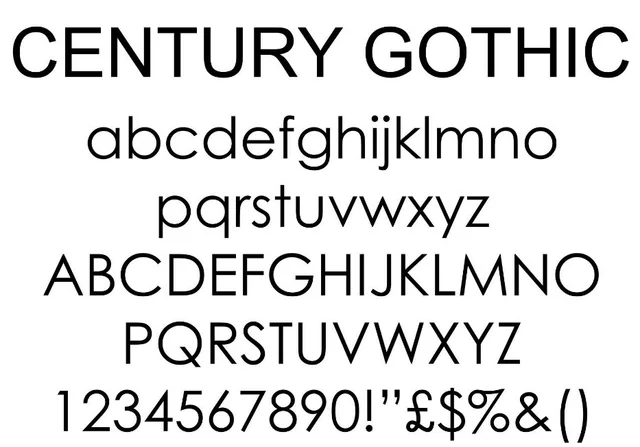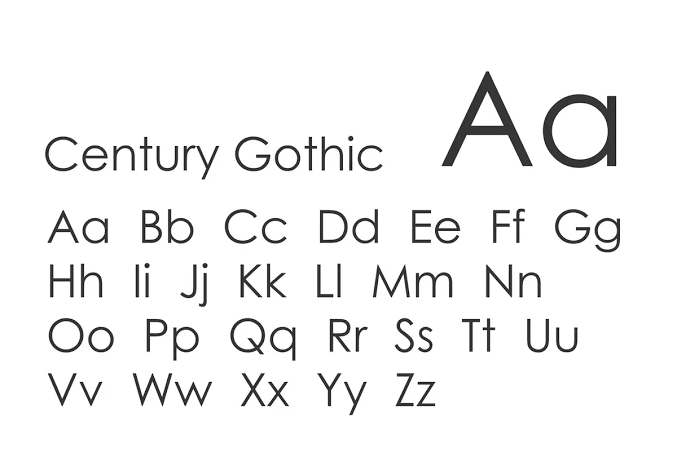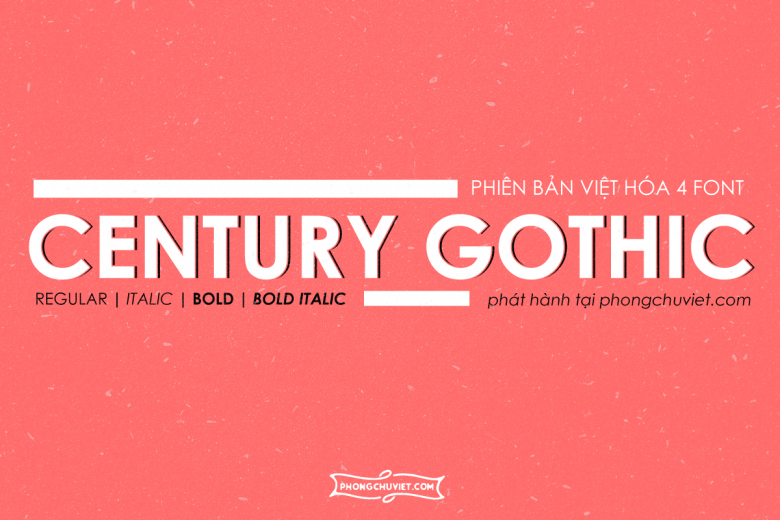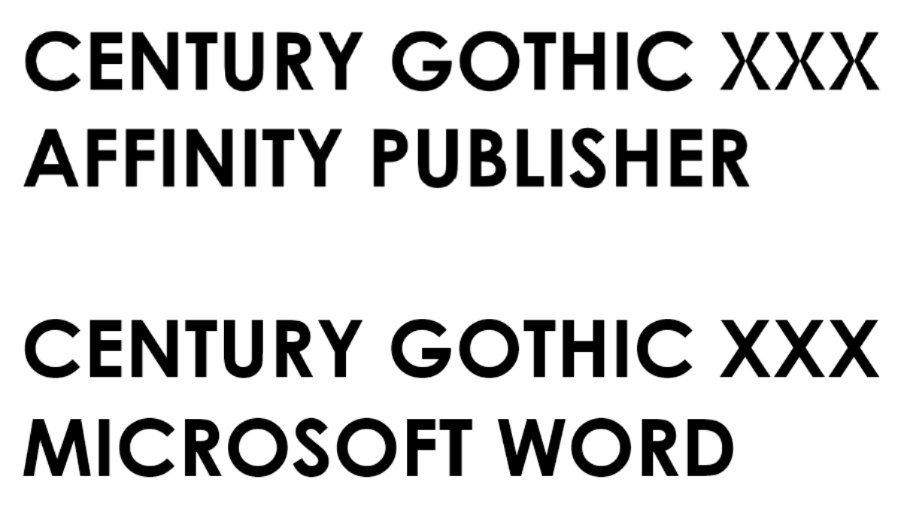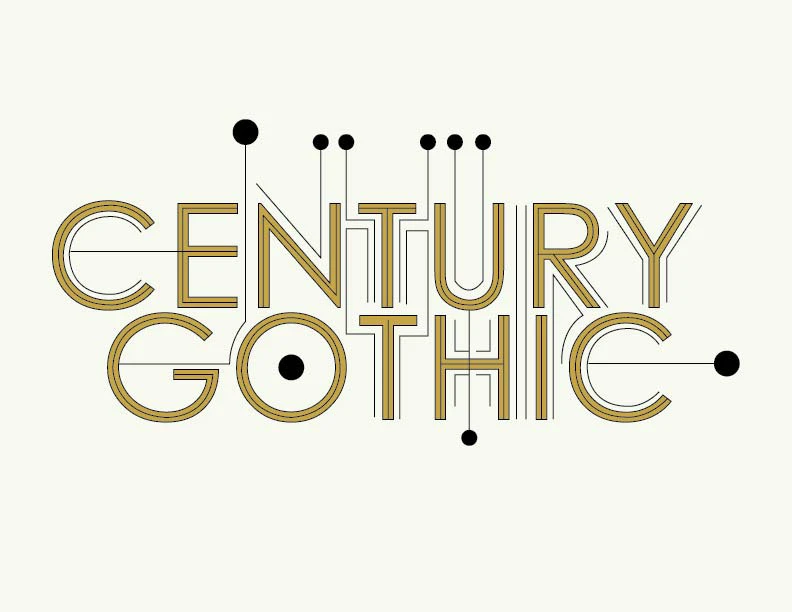
Font chữ Century Gothic Việt hóa là bộ phông chữ không chân (Geometric Sans-serif) hiện đại mang tính biểu tượng, được phát triển bởi Monotype dựa trên phông chữ Twentieth Century kinh điển của Sol Hess. Với cấu trúc chữ xây dựng từ những hình tròn chuẩn xác, độ mở chữ rộng rãi và các đường nét thanh thoát, Century Gothic toát lên vẻ đẹp tối giản, sạch sẽ và cực kỳ thông thoáng trên mọi bề mặt thiết kế. Doozypack.vn cung cấp link tải font Century Gothic Việt hóa chuẩn kỹ thuật, giúp bạn sở hữu phông chữ đẳng cấp mà không lo gặp bất kỳ lỗi hiển thị dấu thanh nào khi thiết kế bao bì và bộ nhận diện thương hiệu.
Đặc điểm thẩm mỹ độc đáo của bộ font Century Gothic
Century Gothic không đi theo sự phức tạp rườm rà của các phông chữ trang trí; nó chinh phục người xem nhờ sự minh bạch, tính kỷ luật của hình học và phong cách tối giản (Minimalism) trường tồn.
Cấu trúc Geometric Sans-serif tinh gọn và chuẩn xác
Đặc trưng lớn nhất của font chữ Century Gothic Việt hóa là các ký tự như ‘o’, ‘c’, ‘d’, ‘p’ được thiết kế dựa trên hình tròn hình học gần như tuyệt đối. Thân chữ thẳng đứng, các nét vẽ có độ dày đồng đều tạo nên một nhịp điệu Typography vô cùng ngăn nắp, hiện đại và chuẩn mực. Khi đặt Century Gothic làm tiêu đề trên bao bì, thương hiệu của bạn sẽ ngay lập tức toát lên vẻ ngoài tân thời, đáng tin cậy và bắt kịp xu hướng đồ họa quốc tế.
Độ mở chữ thoáng đãng với tỷ lệ hình tròn hoàn hảo
Century Gothic sở hữu tỷ lệ x-height lớn cùng các khoảng hở trong chữ (counter) rộng rãi khác thường. Thiết kế này không chỉ giúp phông chữ tiết kiệm diện tích mực in thực tế mà còn duy trì được độ rõ nét đáng kinh ngạc từ màn hình kỹ thuật số cho đến các bản in bao bì thực tế, giúp người xem tiếp nhận thông tin bảng thành phần hay hướng dẫn sử dụng mà không hề bị mỏi mắt.
Ưu điểm nổi bật của bản font Century Gothic hỗ trợ tiếng Việt
Khi ứng dụng các phông chữ hình học quốc tế vào thị trường trong nước, sự chỉn chu về dấu câu là yếu tố quyết định đến tính chuyên nghiệp của bản thiết kế:
- Khắc phục triệt để lỗi dấu tiếng Việt: Phiên bản font Century Gothic hỗ trợ tiếng Việt đã được đội ngũ thiết kế trau chuốt thủ công từng dấu câu. Các dấu sắc, huyền, hỏi, ngã, nặng được vẽ với tỷ lệ cân đối, đặt ở vị trí thoáng đãng so với thân chữ, không gây cảm giác chắp vá hay đè nét làm mất tính thẩm mỹ hình học.
| Biến thể Font | Đặc điểm thị giác | Ứng dụng đề xuất tại Doozypack.vn |
| Century Gothic Regular | Cân đối, thông thoáng, dễ đọc | Dùng cho nội dung hướng dẫn sử dụng, bảng thành phần (Body text). |
| Century Gothic Bold | Dày dặn, vững chãi, nổi bật | Dùng làm tiêu đề chính, tên sản phẩm hoặc logo thương hiệu. |
| Century Gothic Italic | Nghiêng nhẹ, tinh tế, hiện đại | Dùng cho các thông số phụ, trích dẫn ngắn trên bao bì. |